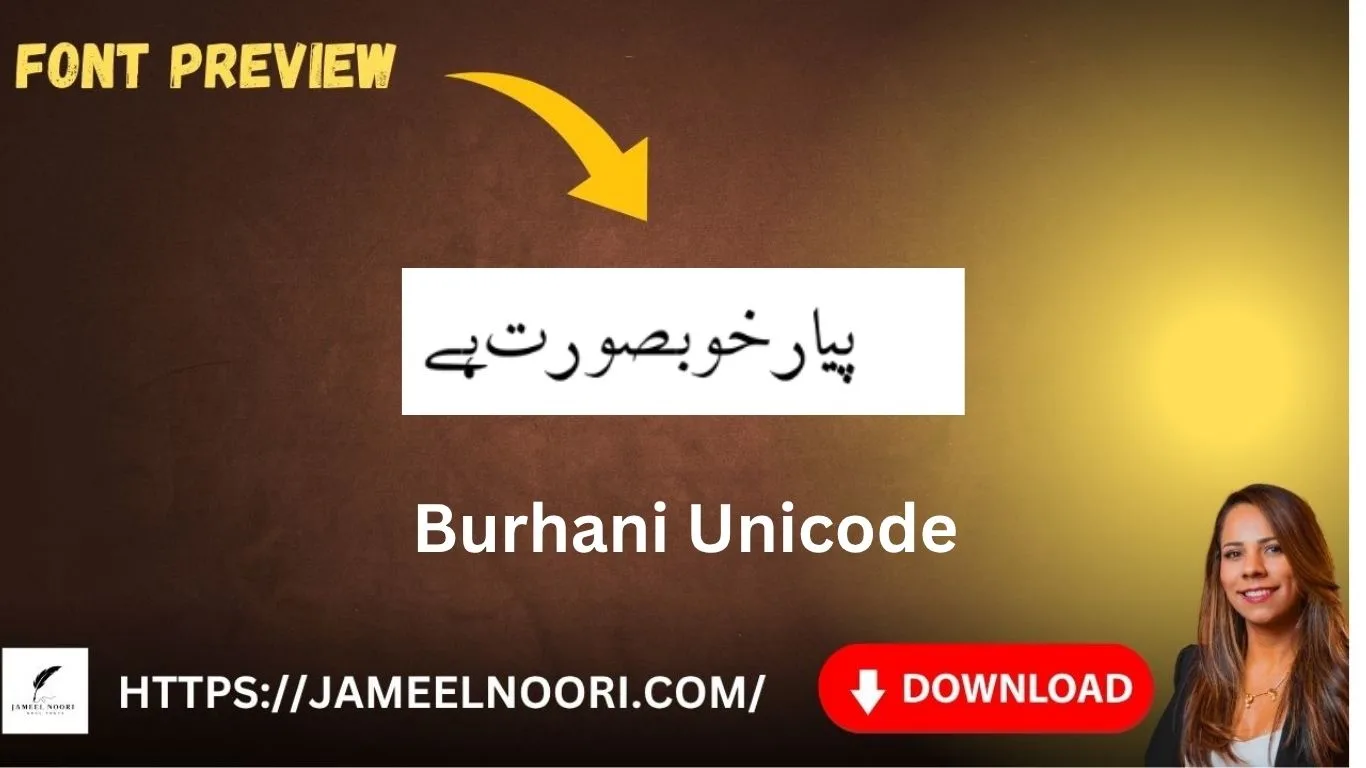
Introduction – Download Urdu Font Burhani Unicode
Agar aap Urdu design, publishing ya phir typing ke liye stylish aur readable font talash kar rahe hain to Burhani Unicode aap ke liye ek zabardast choice ho sakta hai. Ye font un logon ke liye hai jo Urdu script ko clear, professional aur Unicode support ke sath chahte hain. Aayein is font ka detailed review karte hain.
Features of Burhani Unicode Font
✅ Unicode Support
✅ Stylish aur readable design
History and Background
Burhani Unicode font aik aisa Urdu typeface hai jo khas tor par Urdu ki khubsurti aur readability ko madde nazar rakhte hue design kiya gaya hai. Is font ne kai designers aur Urdu lovers ka dil jeet liya hai. Font ke naam se zahir hai ke is font ka taluq Dawoodi Bohra community ke “Burhani” design culture se hai.
Benefits of Using Burhani Unicode Font
✅ Behtareen Urdu readability
✅ Unicode support ke wajah se website aur mobile app development mein asani
✅ Professional looking documents aur designs ke liye perfect
Why Choose Burhani Unicode?
Aaj kal Urdu likhne ke liye market mein bohat se fonts available hain, lekin Burhani Unicode font ki apni ek alag pehchaan hai. Yeh font khas tor par un logon ke liye design kiya gaya hai jo Urdu mein likhne ke liye modern technology aur compatibility ko importance dete hain.
✅ Unicode Support
Sab se pehli aur sab se badi wajah yeh hai ke Burhani Unicode ek Unicode-compliant font hai. Iska matlab yeh hai ke aap is font ko har aise platform par use kar sakte hain jo Unicode ko support karta ho — jaise:
Yeh flexibility dusre legacy Urdu fonts (like InPage fonts) mein nahi milti.
✅ Best For Web & App Development
Agar aap Urdu content wali website, blog ya koi mobile app bana rahe hain to Burhani Unicode font aap ke liye best choice hai. Kyunke yeh font search engine friendly hai aur har device par consistent nazar aata hai — chahe screen mobile ki ho ya desktop ki.
✅ Accurate Display of Every Urdu Character
Is font mein Urdu ke tamam alphabets, harakaat (zabar, zer, pesh), aur khas characters ko accuracy ke sath design kiya gaya hai. Yeh font aapke text ko professional aur readable banata hai, jisse reader ka experience bohat behtar hota hai.
✅ Perfect for Urdu Blogging & Digital Writing
Agar aap Urdu blogging karte hain ya kisi digital Urdu magazine, article, ya e-book par kaam kar rahe hain to yeh font aapki presentation aur readability ko enhance karta hai. Yeh font blogging aur digital publishing ke liye specially recommend kiya jata hai.
Common Use Cases
- Urdu Literature Publishing
- Urdu News Graphics
- CVs and Professional Documents
- Islamic Typography
- Urdu Mobile Apps and UI
Does it include English characters?
Yes, basic English letters include hain, lekin yeh mainly Urdu ke liye optimized hai.